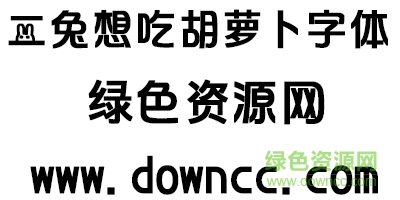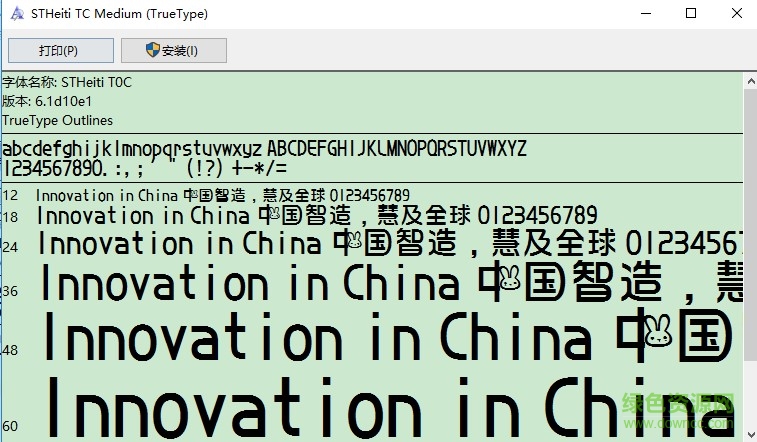
二兔想吃胡蘿卜字體是一款非??蓯?ài)的藝術(shù)字體,這款字體上帶有兔子的圖案,看起來(lái)非常的天真可愛(ài),可以適用于藝術(shù)設(shè)計(jì)、卡通漫畫(huà)等領(lǐng)域,喜歡的朋友歡迎來(lái)綠色資源網(wǎng)下載使用!
二兔想吃胡蘿卜字體與指尖花涼體風(fēng)格極其相似,但整體造型更加隨意,同樣活潑可愛(ài)的筆觸讓文字更加生動(dòng)活潑,給大家的包裝設(shè)計(jì)、平面設(shè)計(jì)等帶來(lái)更多美感!